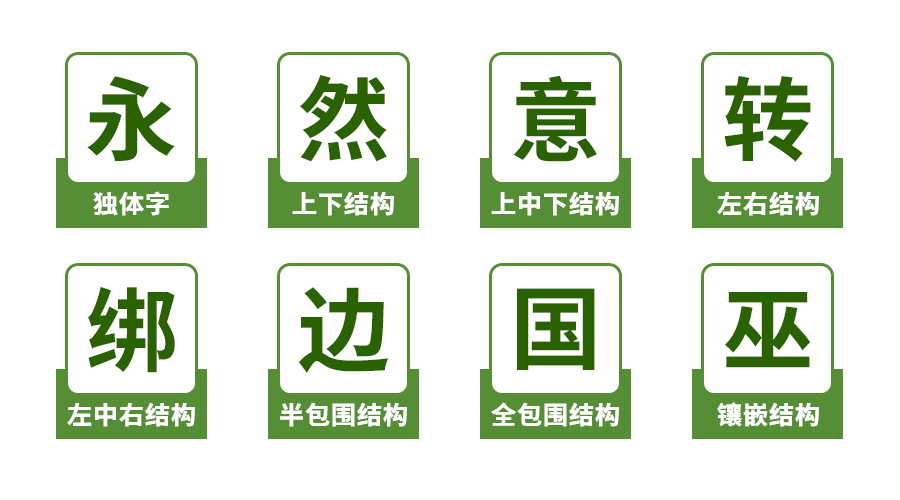
汉字的种类繁多,笔画数量各异,这使得字体设计的空间布局显得尤为重要。在字体的构造上,可以将其间架结构划分为两大类:独体字与合体字。
独体字是指由笔画组成、不能或不宜再进行拆分、可以构成合体字的汉字。因为这类字是从图画演变而成的,所以每一个字都是一个整体。在设计这类结构的字时,要注意笔画到位,主次分明。
合体字由两个或两个以上的部件组合而成的汉字结构。合体字在组合的成分上分为会意字和形声字,常见的合体字结构包括左右结构、上下结构、左中右结构、上中下结构、半包围结构、全包围结构和镶嵌结构等。